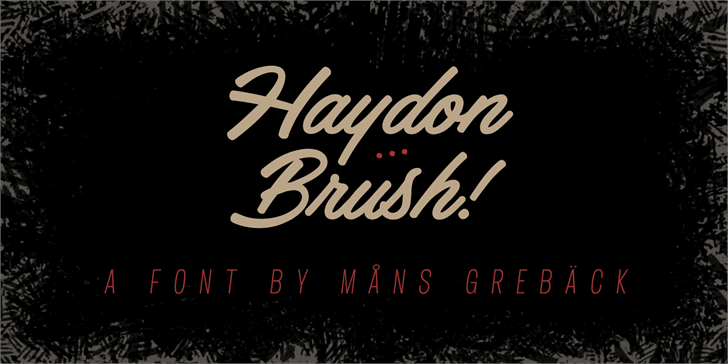
A Haydon Brush Font é uma deliciosa aposta para designers que buscam uma mão-dobrada elegante para seus projetos digitais. Com traços achatados e uma caligrafia suave, ela traz um ar descontraído e amigável à sua identidade visual. Seja para criar cartões de visita minimalistas ou designs gráficos com um toque autêntico, esta fonte certamente fará seu trabalho. O designer Måns Grebäck criou a Haydon Brush, fornecendo uma opção única e distintiva na categoria de fonts brush. Esta particularidade da Haydon Brush tem sido adorada por designers que desejam dar vida ao design de suas criações com um estilo moderno e versátil. Para aqueles que buscam a Haydon Brush Font, o designer Måns Grebäck está disponível para responder a qualquer questão ou propor a melhor opção comercial. Visite o site www.mansgreback.com/haydon-brush para mais detalhes.
Designer: Måns Grebäck